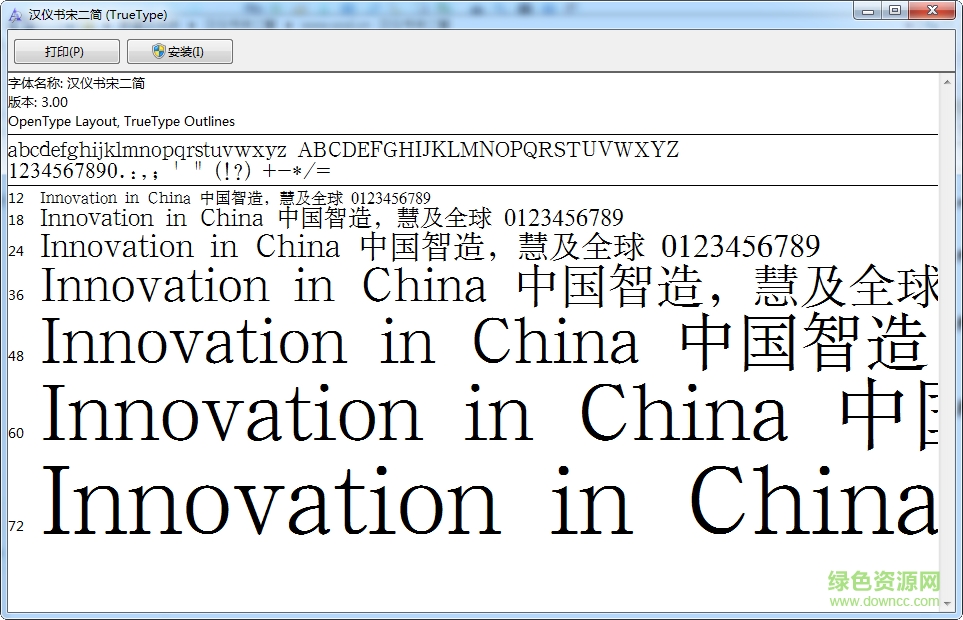
漢儀書宋二簡(jiǎn)繁字體包含了書宋二簡(jiǎn)體和繁體兩種選擇,漢儀書宋二是一款非常端正的中文字體,適合在正式的場(chǎng)合來進(jìn)行使用,適合應(yīng)用于廣告設(shè)計(jì)、名片設(shè)計(jì)、包裝印刷、產(chǎn)品設(shè)計(jì)等應(yīng)用。歡迎來綠色資源網(wǎng)下載。